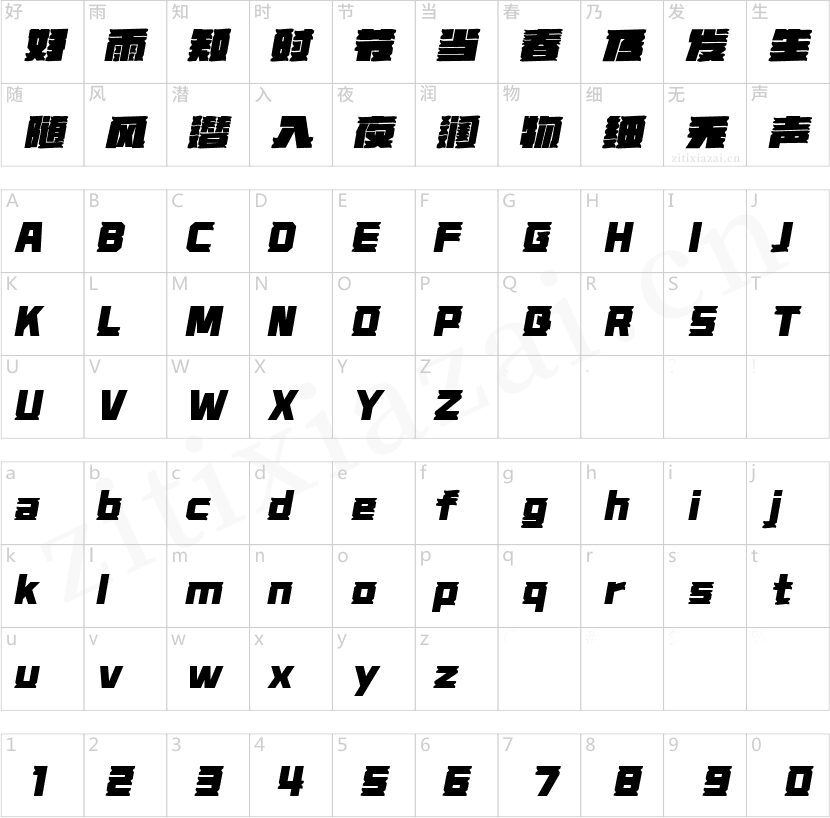
字魂神奇冒险家
字魂神奇冒险家是一款艺术字体,深受广大设计师的喜爱。
字体设计说明
字魂字体字魂神奇冒险家字体是由字魂创意字库设计并生产的一款可商用的字体,被收录于字魂先锋系列。该字体支持GB-2312标准,包含6942个中文、字母、符号和数字,字体类型偏向创意字体,具有动漫、可爱的风格,在市面上广泛用于游戏动漫、视频影视、餐饮食品等场景。